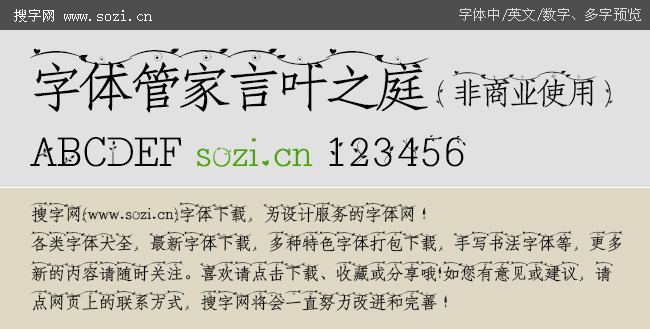
字體管家言葉之庭(非商用版)
搜字網(wǎng)給大家提供一款字體管家言葉之庭(非商用版)中文字體下載,該字體是一款以宋體為原形的藝術(shù)字體,字體上裝飾了花紋,使簡(jiǎn)潔的宋體帶了一分趣味,適合書(shū)裝設(shè)計(jì)、海報(bào)設(shè)計(jì)等應(yīng)用(此字體為個(gè)人非商用版,商用請(qǐng)購(gòu)買(mǎi)授權(quán))。